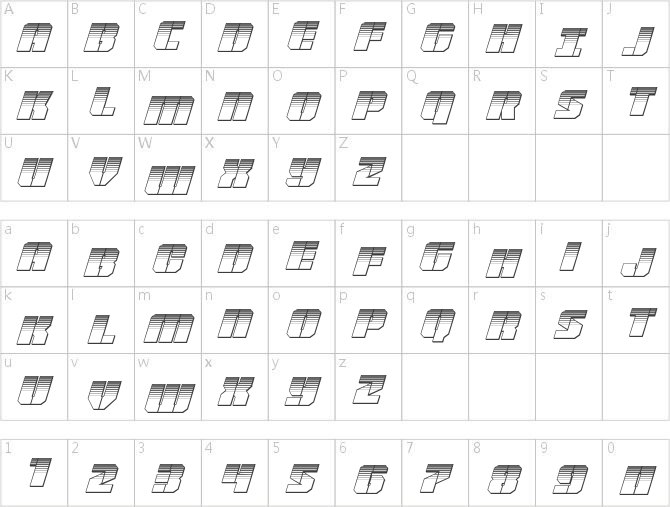
Warp Thruster Platinum Italic
Warp Thruster Platinum Italic介绍
Warp Thruster Platinum Italic字体字库是一款让人赏心悦目、百看不厌的英文字体,适合各类广告和产品包装设计应用,字体大小0.09MB,格式为ttf字体,上传用户是哼哼哈兮,作者/版权方为未知